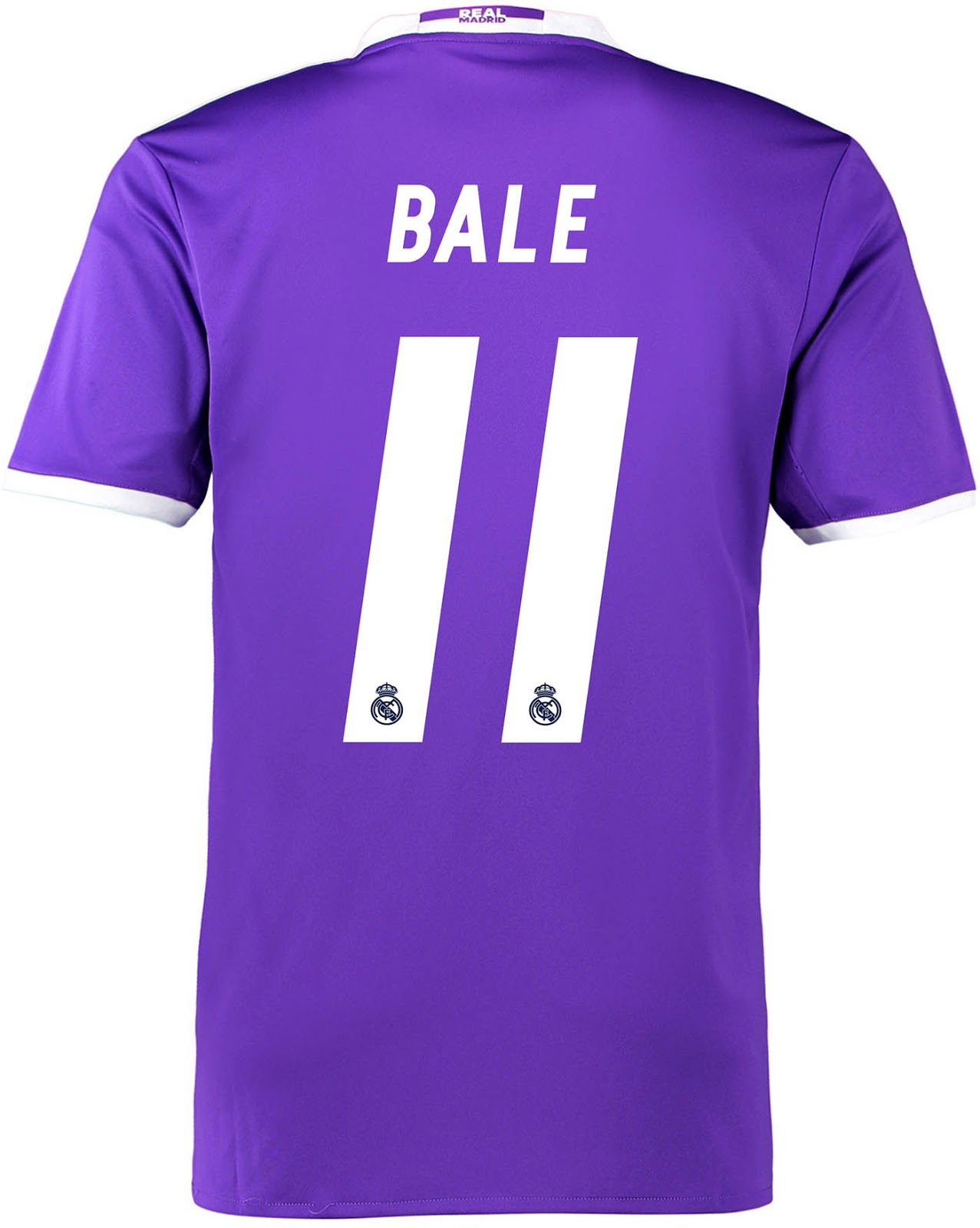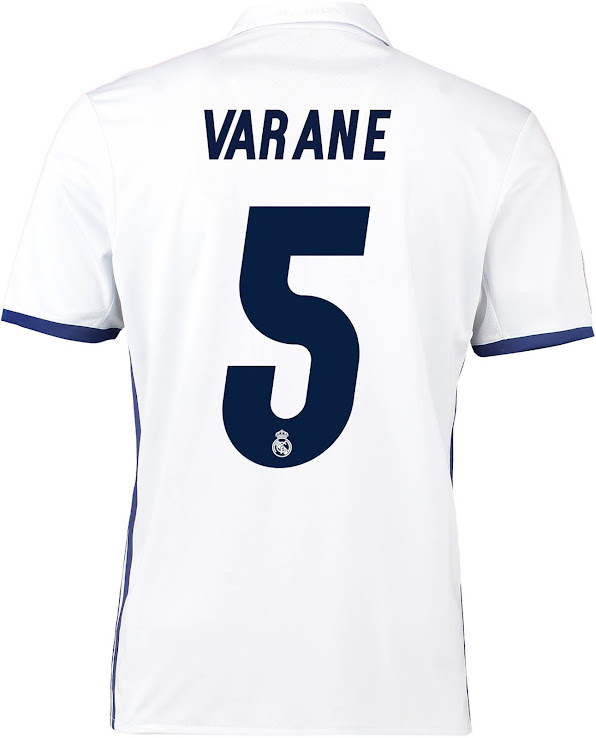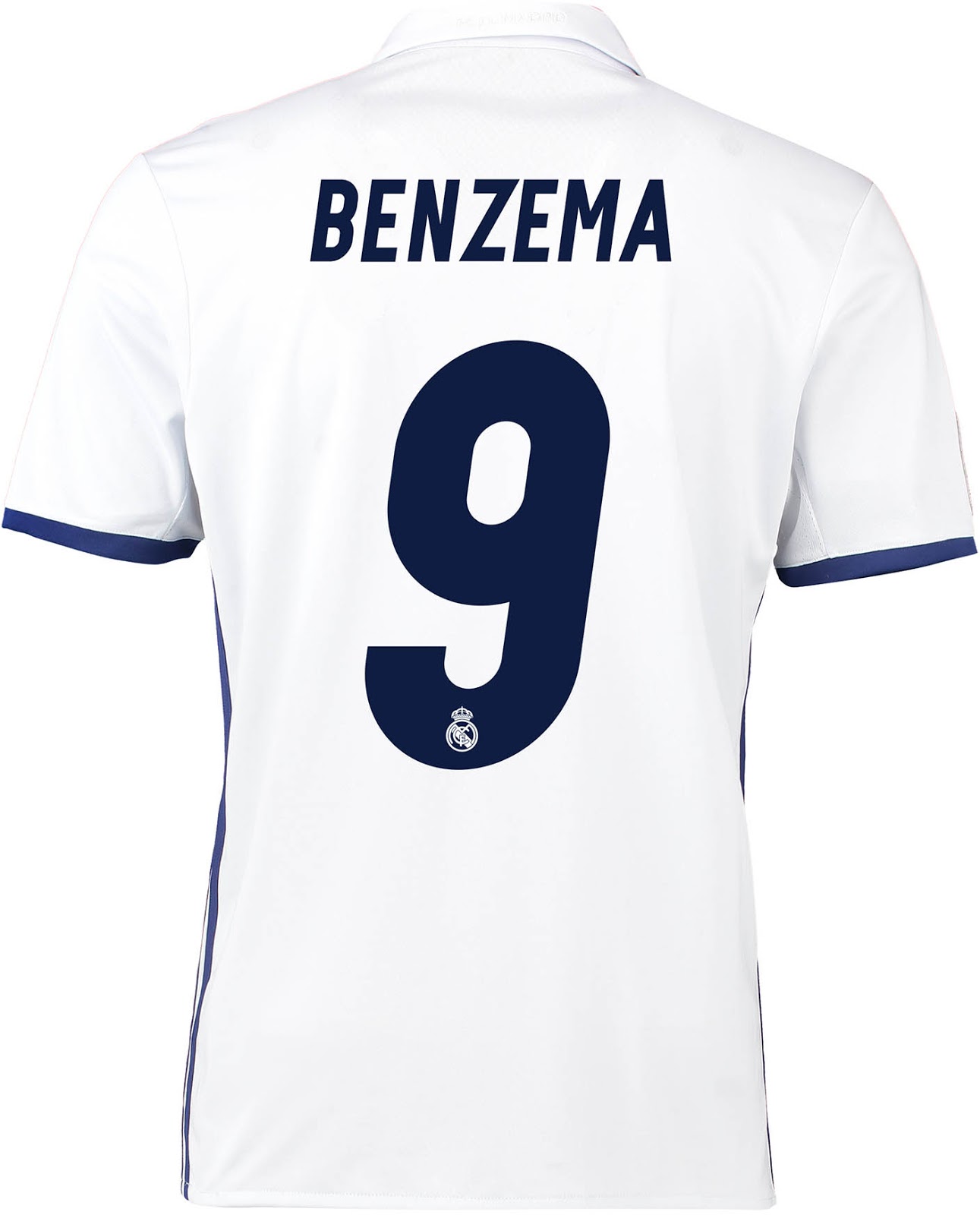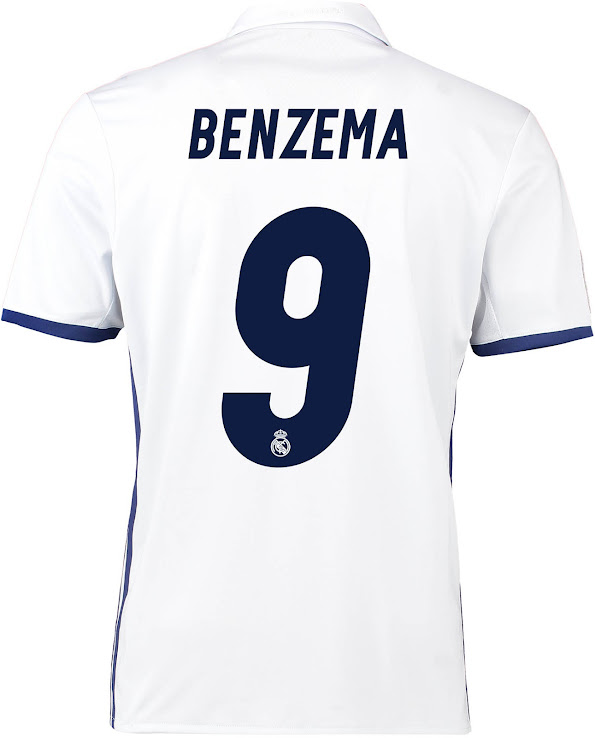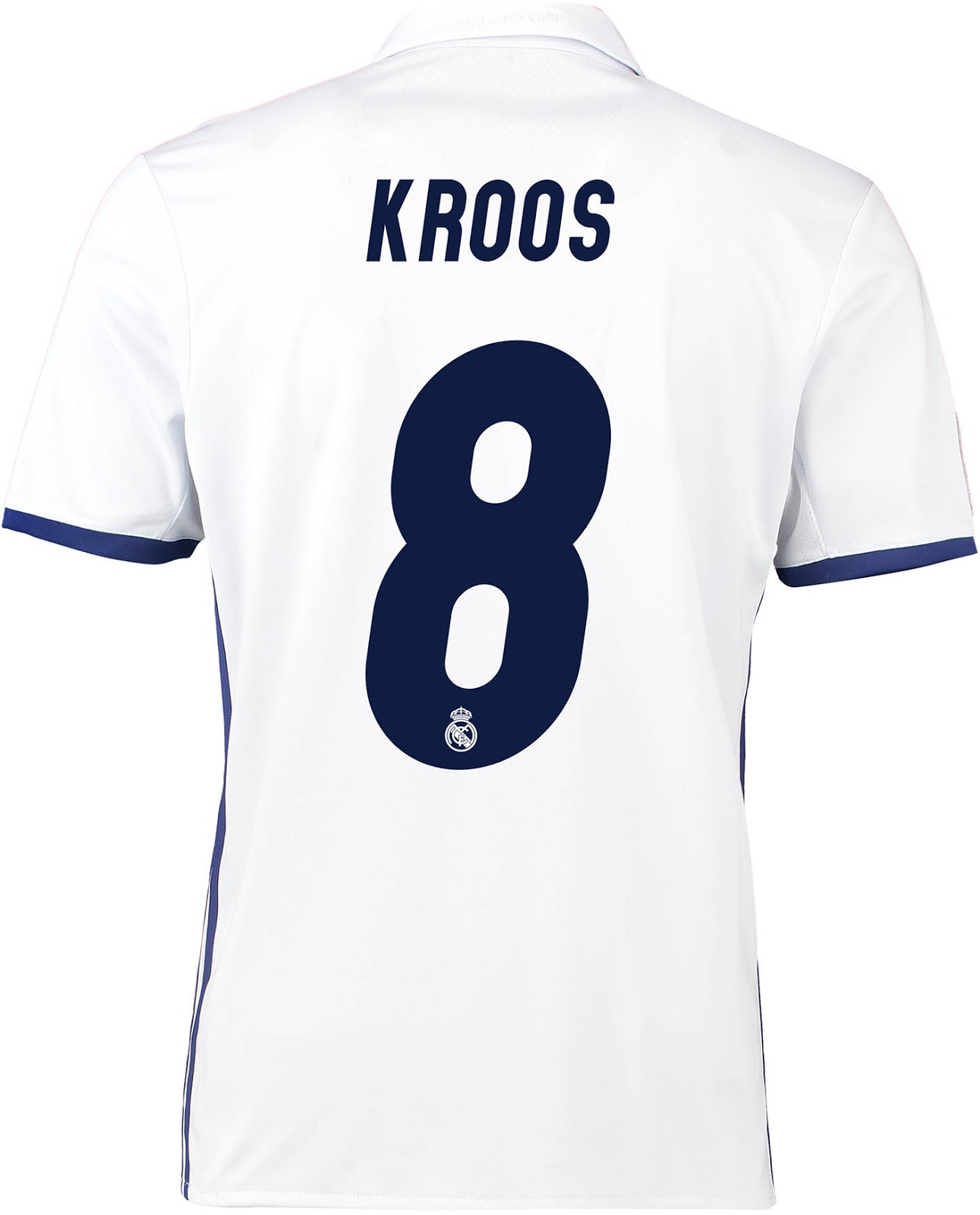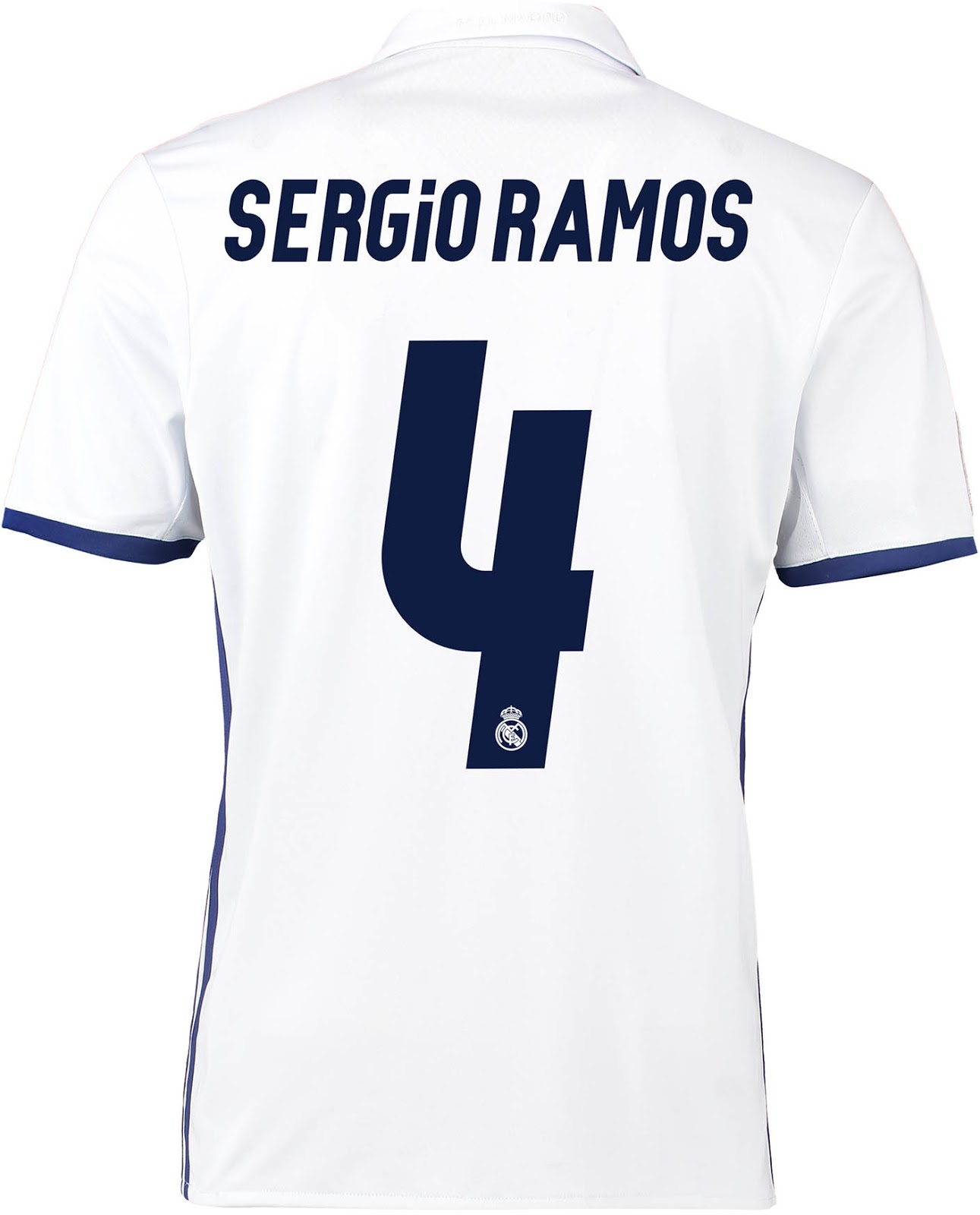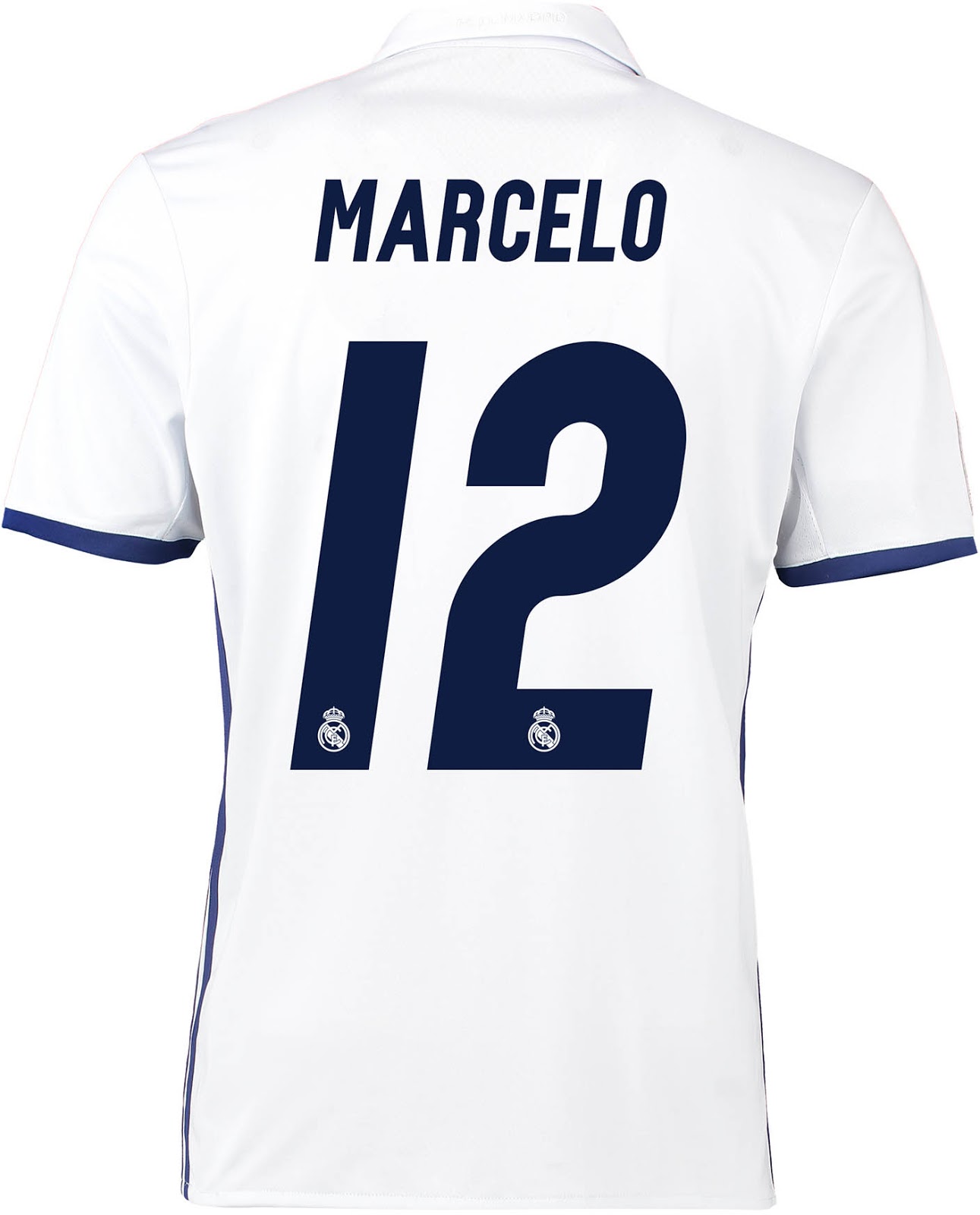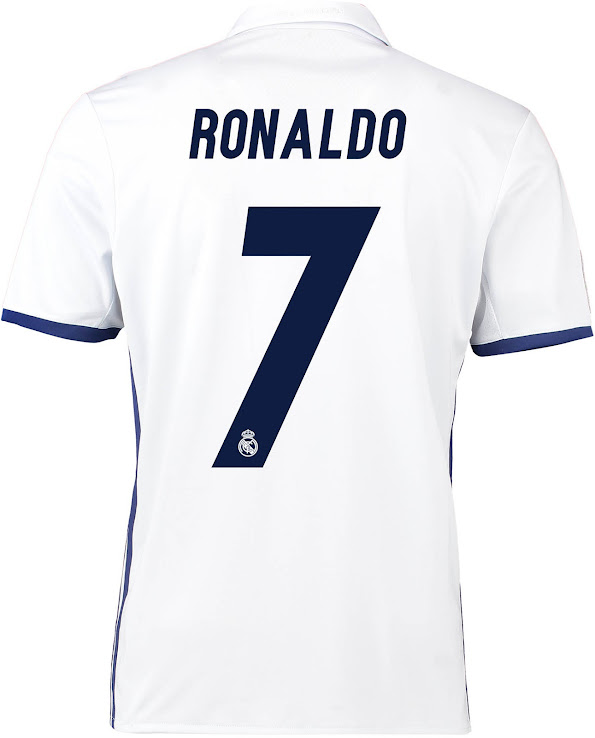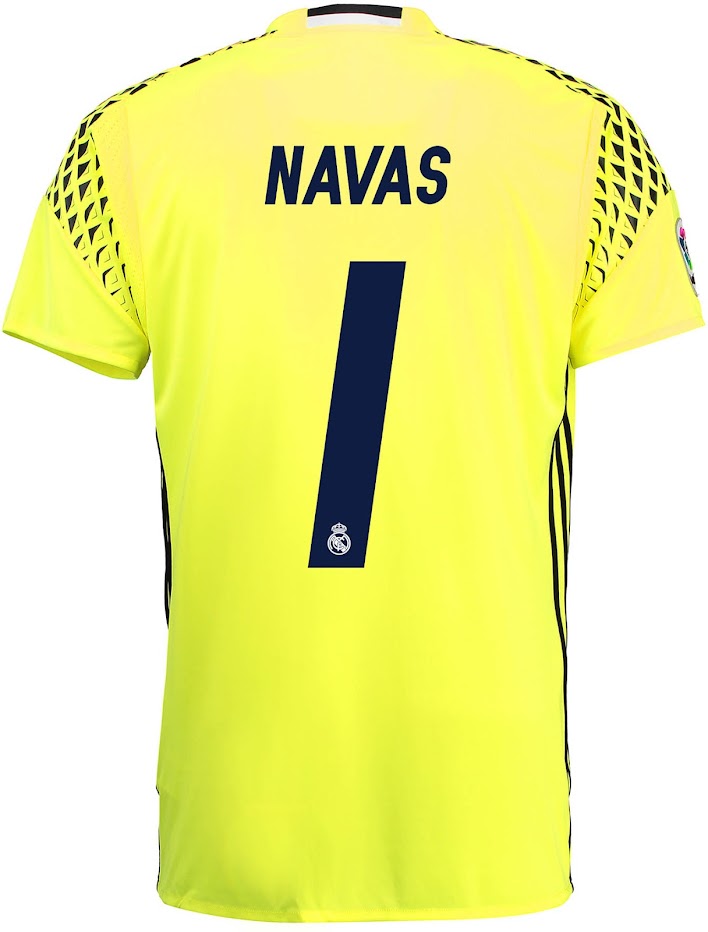
Adidas Real Madrid 16-17 Schriftart enthüllt
Die neue Real Madrid 16-17 Schriftart wurde von manchen von Real Madrids Schriftarten der 2000er inspiriert. Die Real Madrid 2016-17 Schriftart hat ein modernes Design.
Adidas Real Madrid 16-17 Trikot-Schriftart
Das ist die neue Schriftart, die von Adidas für die neuen Real Madrid 16-17 Trikots entworfen wurde.
Die neue Real Madrid 16-17 Schriftart, die von Real Madrids kursiver Schriftart, die in der Saison 2005-06 verwendet wurde, inspiriert wurde, weist einen modernen, einzigartigen und sauberen Ansatz auf.
Die neue Adidas Real Madrid 16-17 Schriftart hat einen sehr klassischen Look, wobei das Real-Madrid-Logo am unteren Ende platziert ist.
Die neue Real-Madrid-Schriftart wird in allen Wettbewerben getragen, einschließlich der Champions League, in der der Klub versuchen wird, La Duodecima zu erringen - den 12. Champions-League-Titel.